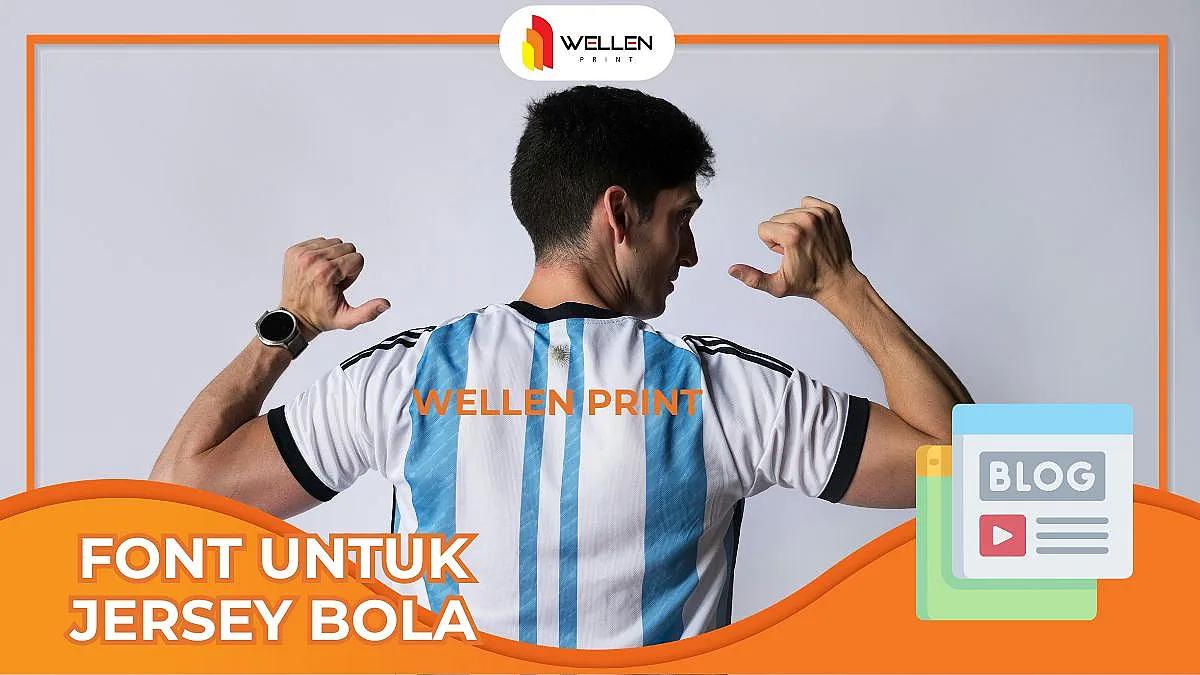
Rekomendasi Font Jersey Bola Terbaik: Tips Pilih Tipografi yang Ikonik
Dalam desain jersey sepak bola, nomor punggung dan nama pemain bukan sekadar identitas, melainkan elemen estetika yang sangat krusial. Pemilihan font jersey bola yang tepat dapat memberikan kesan modern, klasik, garang, atau bahkan futuristik pada seragam tim Anda.
Setiap liga top dunia biasanya memiliki karakteristik font yang berbeda-beda. Berikut adalah pengelompokan gaya font yang sering digunakan:
Ini adalah gaya yang paling umum digunakan dalam olahraga. Font ini memiliki sudut-sudut yang tegas (biasanya 45 atau 90 derajat) dan memberikan kesan kuat serta kokoh.
Karakter: Tegas, tradisional, dan mudah dibaca dari kejauhan.
Contoh Populer: Font ala Varsity atau font Premier League era klasik.
Font ini biasanya memiliki garis yang lebih ramping, kurva yang unik, atau bahkan lubang-lubang ventilasi di dalam angka (perforated).
Karakter: Dinamis, cepat, dan berteknologi tinggi.
Contoh Populer: Font yang digunakan tim nasional pada turnamen Piala Dunia atau font klub besar seperti Manchester City dan Real Madrid versi terbaru.
Font ini seringkali memiliki detail tambahan seperti garis tipis di tengah (inline) atau bayangan (drop shadow) yang memberikan kesan nostalgia tahun 80-an atau 90-an.
Karakter: Elegan, bersejarah, dan berkarakter.
Berikut adalah beberapa nama font (atau tipe serupa) yang sering dicari oleh desainer jersey:
Premier League Font: Memiliki desain yang sangat standar namun sangat ikonik. Sangat direkomendasikan jika Anda ingin tampilan yang profesional.
Adidas World Cup Series: Adidas sering mengeluarkan font dengan garis-garis tajam yang memberikan kesan agresif.
Jersey Sharp: Font dengan ujung-ujung yang tajam, memberikan kesan "predator" dan kecepatan.
Bebas Neue: Font yang simpel, bersih, dan memanjang ke atas. Sangat cocok untuk nama pemain agar terlihat rapi.
Agency FB: Font dengan gaya kotak yang modern, sering digunakan untuk tim-tim futsal modern.
Agar hasil sablon nama dan nomor punggung Anda maksimal, perhatikan hal-hal berikut:
Legibilitas (Keterbacaan): Pastikan angka tidak terlalu rumit. Penonton dan wasit harus bisa mengenali nomor pemain bahkan dari jarak jauh saat pemain sedang bergerak cepat.
Kontras Warna: Pilih warna font yang kontras dengan warna dasar jersey. Jika jersey bermotif ramai, pertimbangkan untuk memberikan outline pada font.
Ukuran Proporsional: Standar tinggi nomor punggung dewasa biasanya berkisar antara 25-28 cm, sedangkan untuk nama sekitar 5-7 cm.